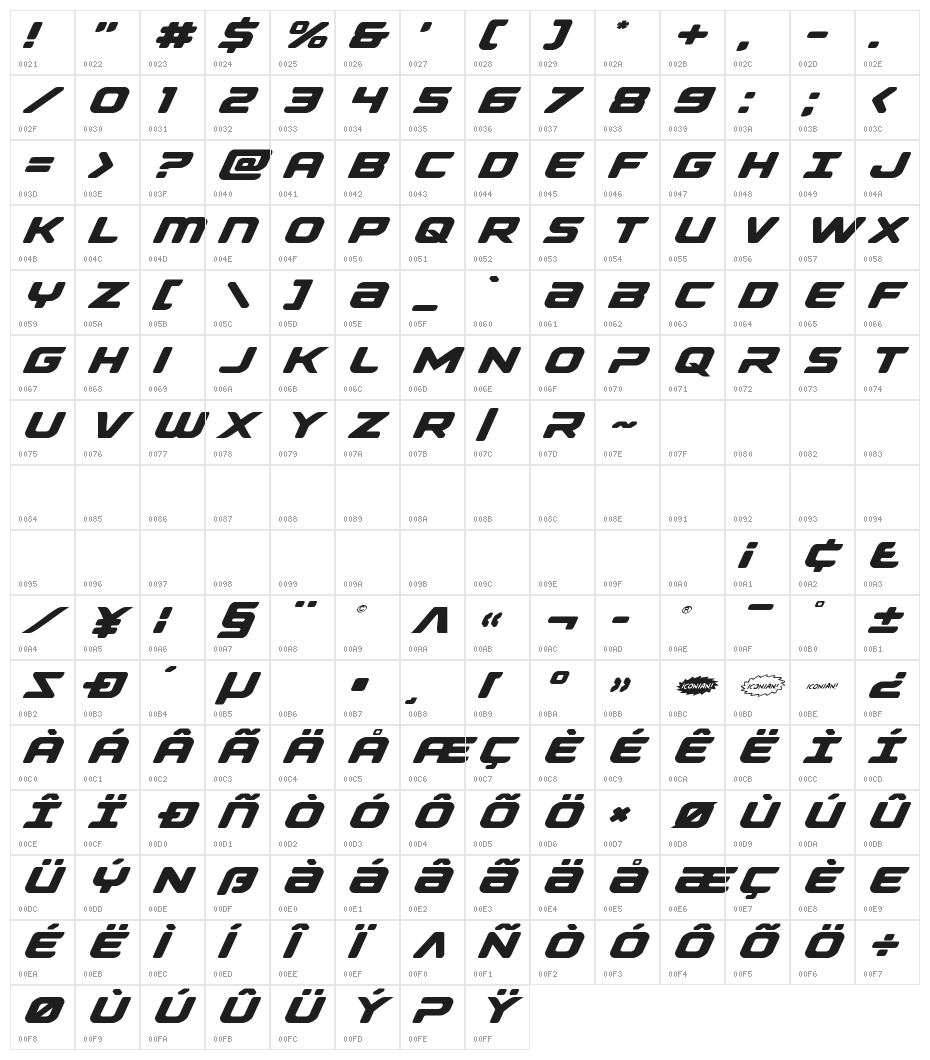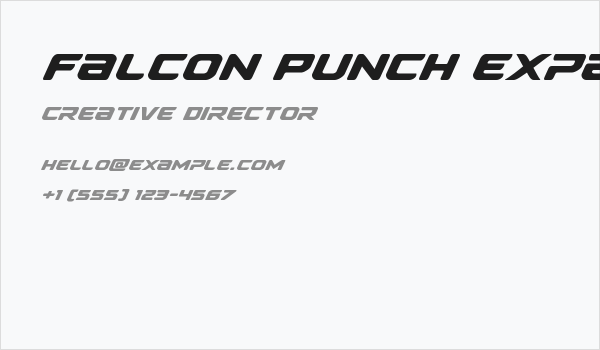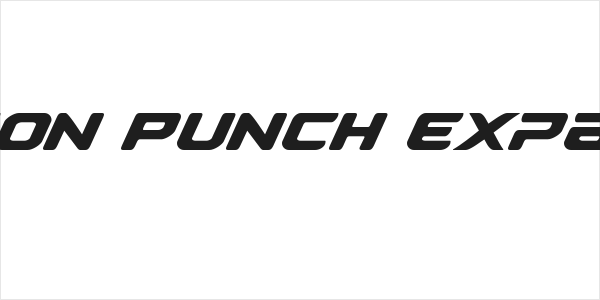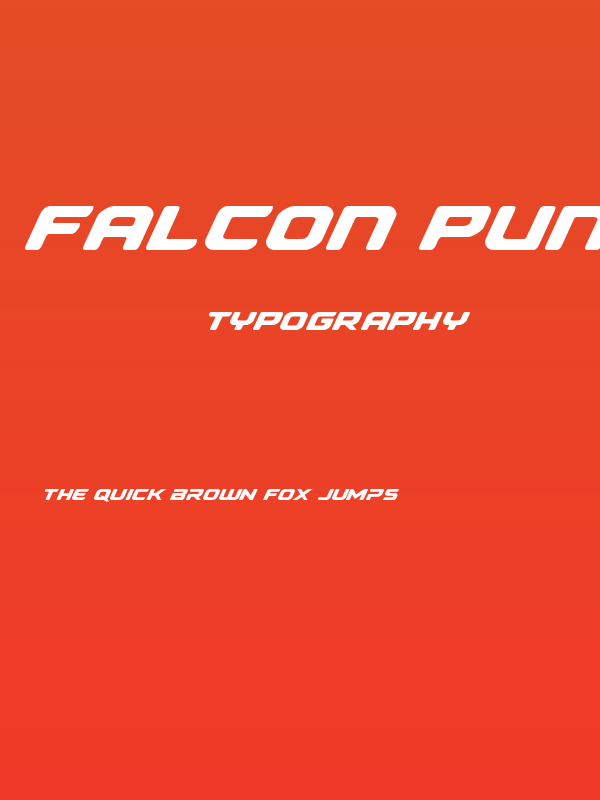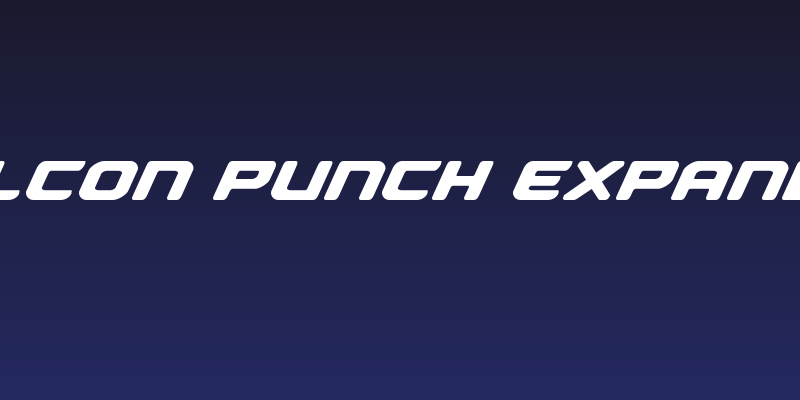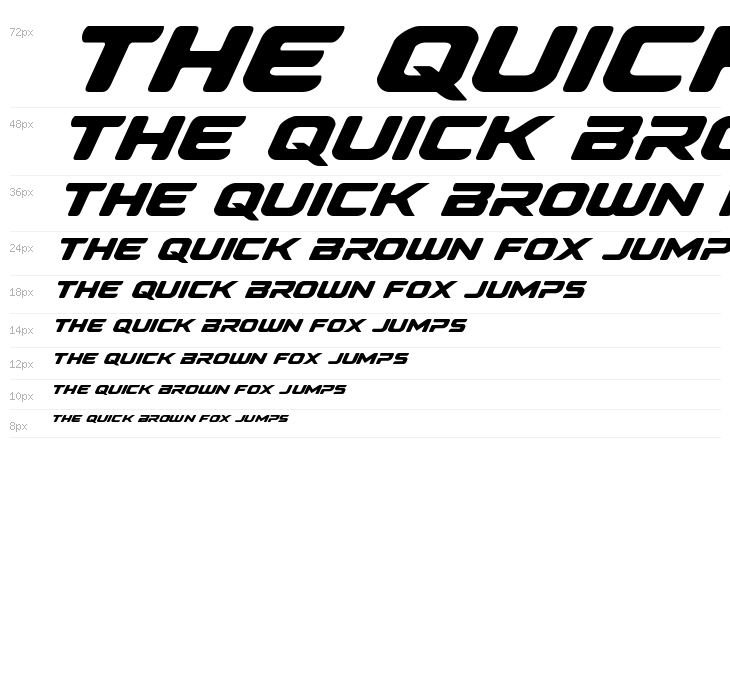
Falcon Punch Expanded Font
| 使用场景 | Headlines, Logos, Digital Interfaces |
| 推荐项目 | Ideal for technology branding, sports team logos, video game titles, and modern advertising campaigns. |